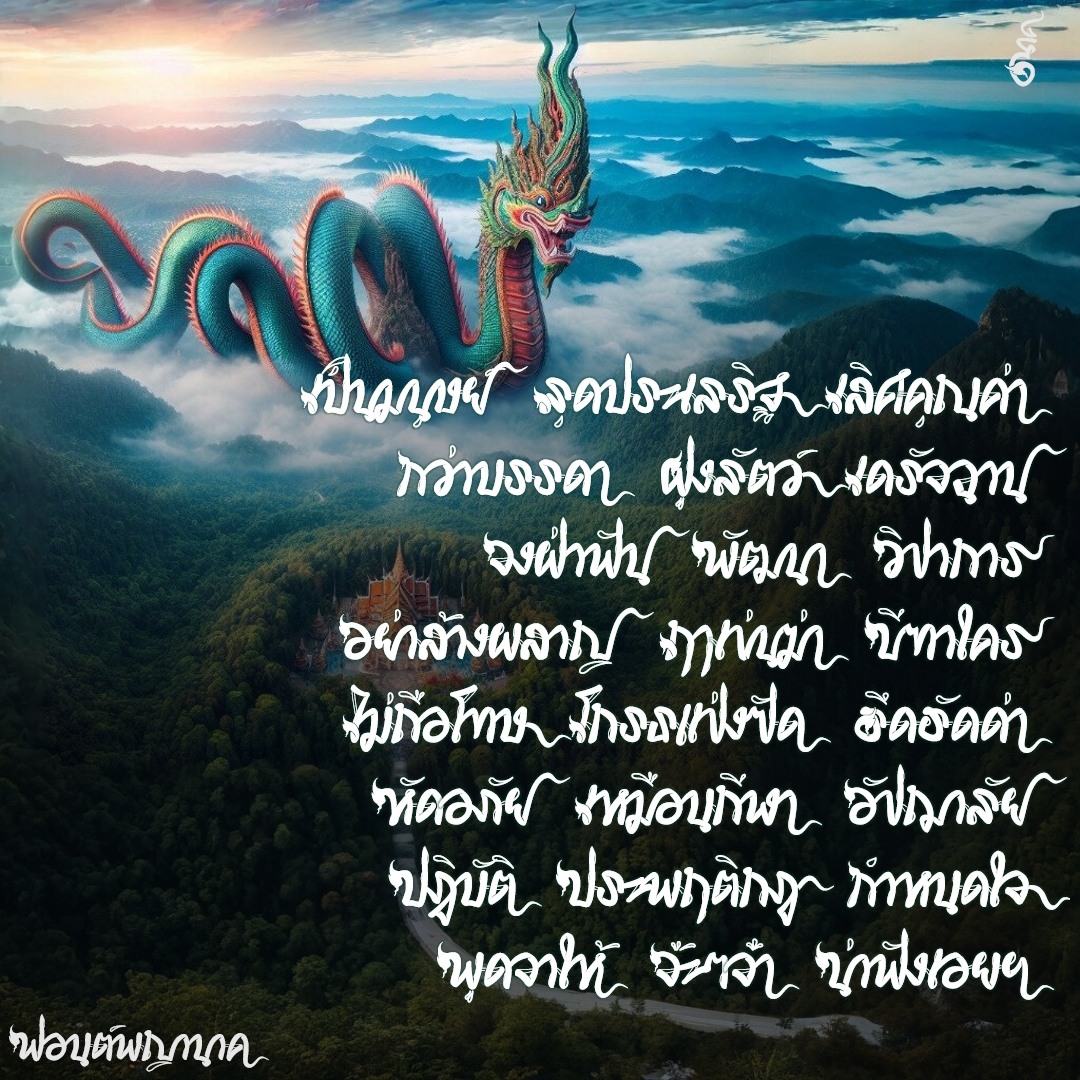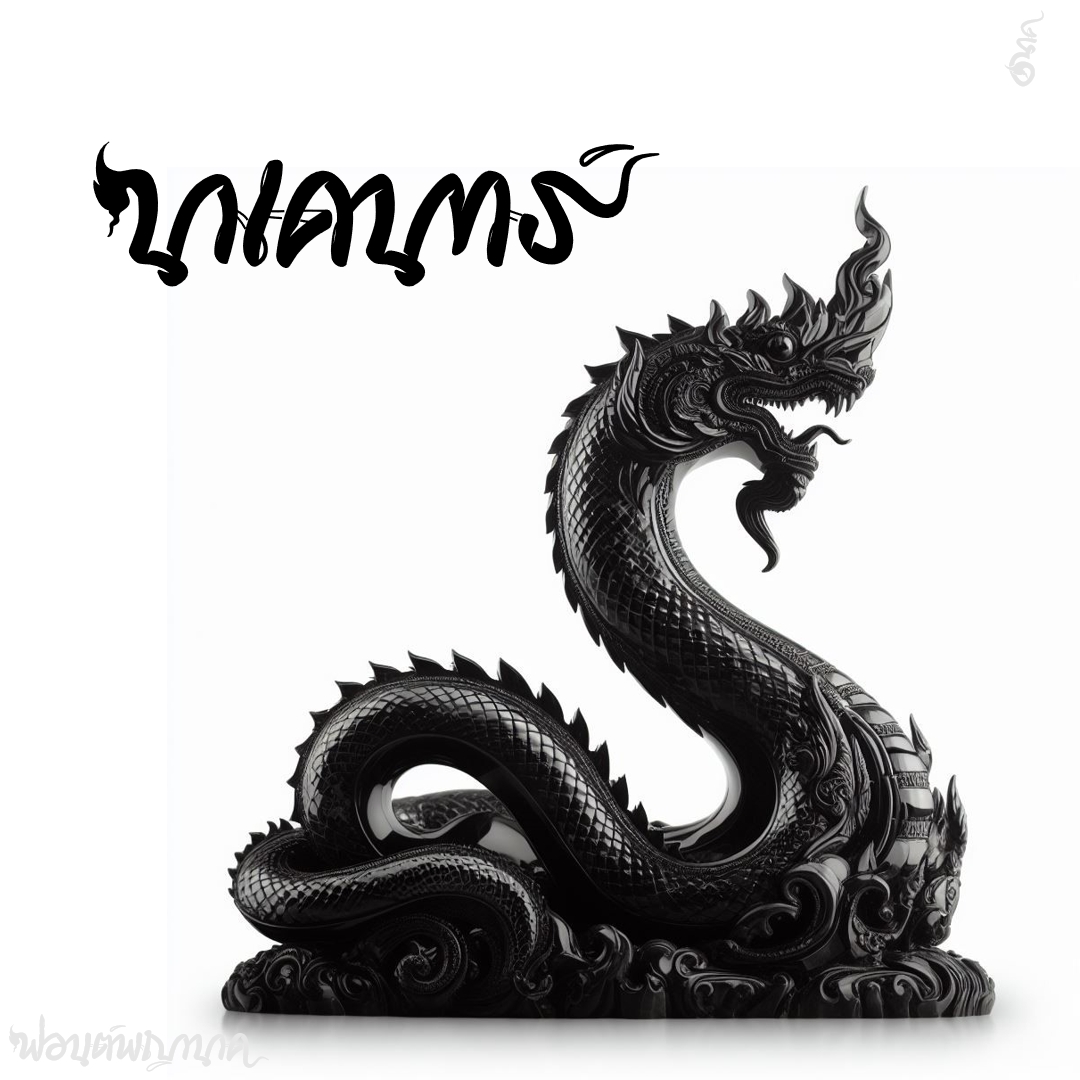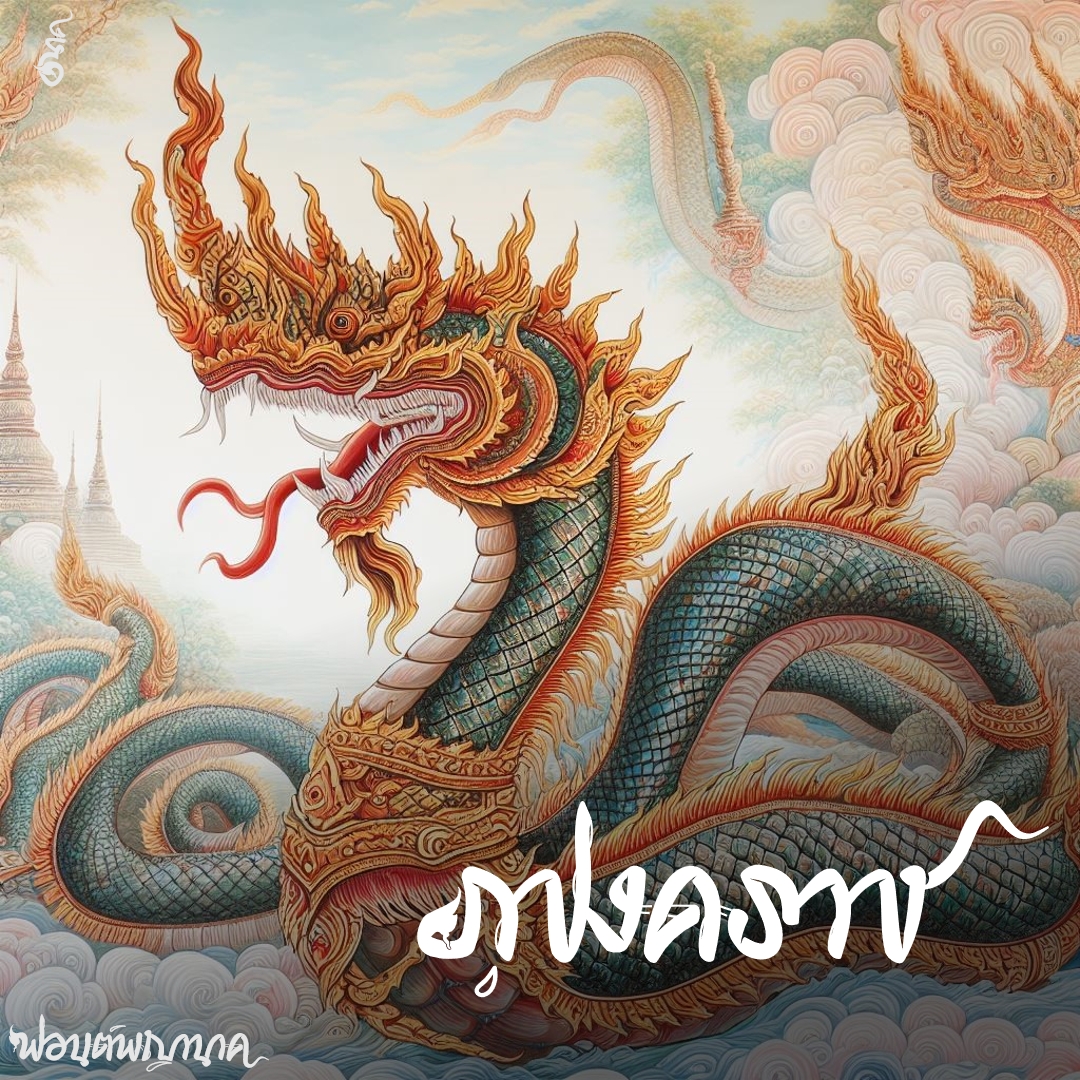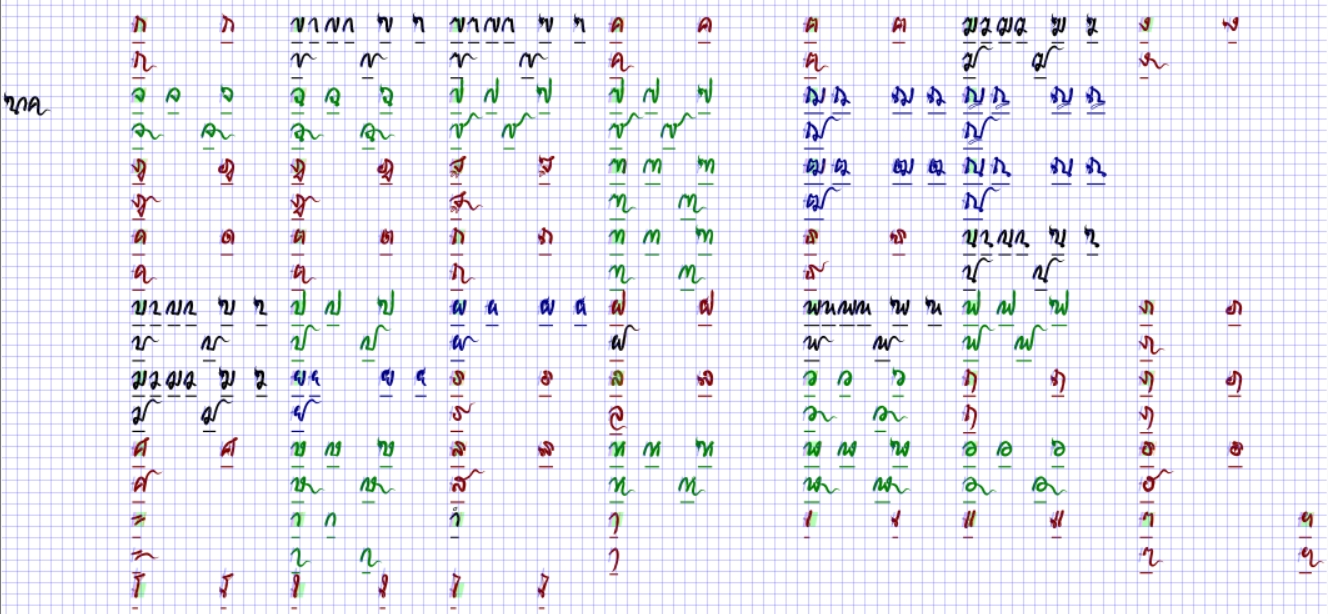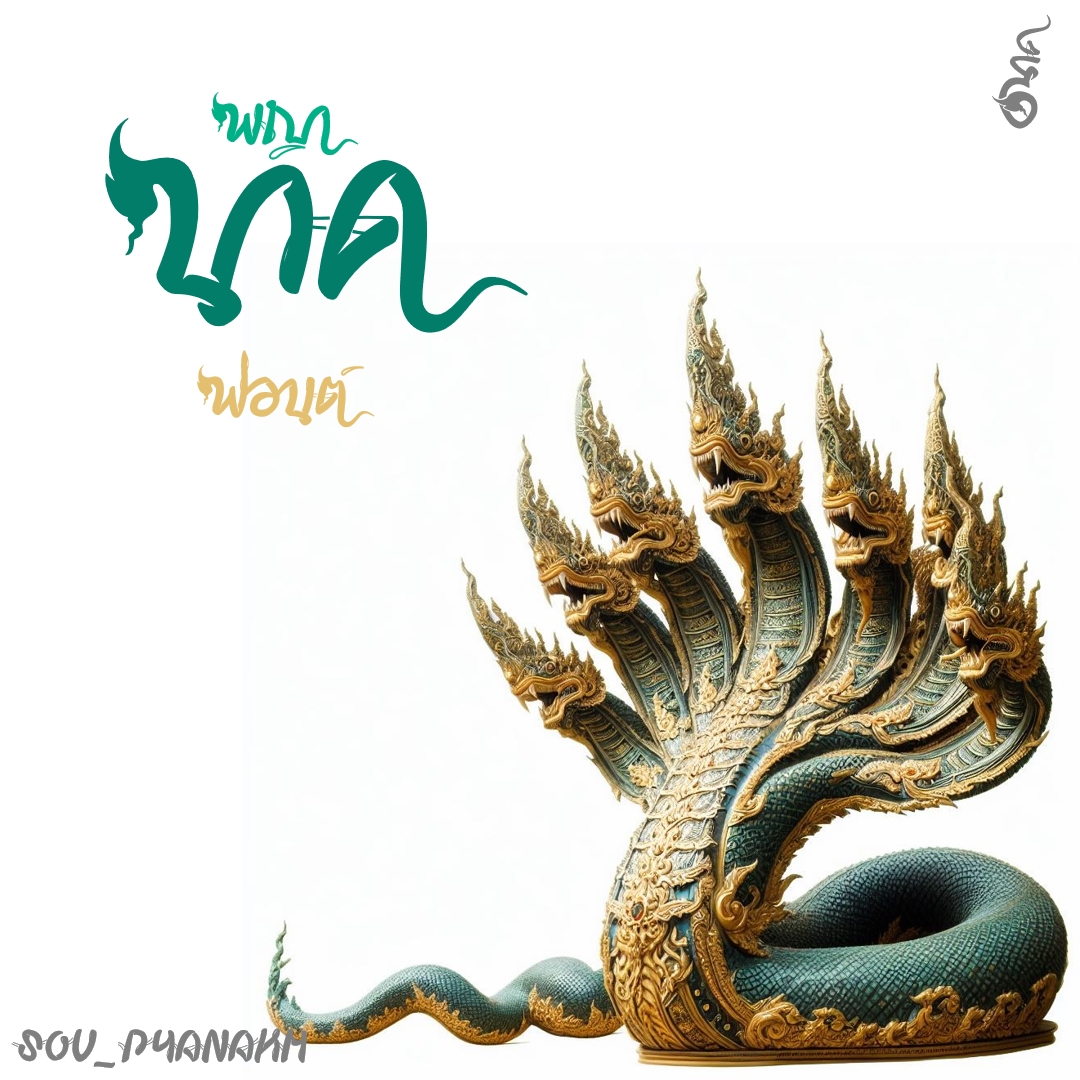
ฟอนต์ พญานาค
ฟอนต์พญานาค ลากเส้นเดียวตั้งแต่หัวถึงหาง
ชื่อฟอนต์ : พญานาค
ฟอนต์พญานาค ลากเส้นเดียวตั้งแต่หัวถึงหาง
ปรับอักษรจาก 3 รูปแบบ เป็น สูงสุด 8 รูปแบบ
เพิ่มฟังก์ชัน จาก 9 เป็น 192